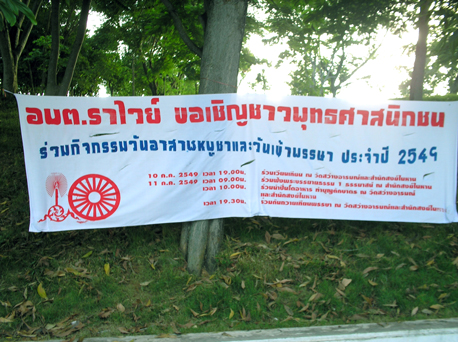
ไปเจอ [ฟอนต์ iannnnn] มา
ไปเจอมาด้วยคน
สถานที่ แถวๆหาดราไวย์ ภูเก็ต เจอเมื่อวันเสาร์
เ็ห็นว่าไกลดี และเป็นสิริมงคลดี
เพิ่งเจอเมื่อวานซืน โฆษณาของรพ.กรุงเทพคริสเตียน เขาใช้iannnnnUBCกัน... เอามาแผ่นนึง เดี๋ยวไปถ่ายรูปก่อน
แล้วก็อีกอัน SOS เจอบนแผ่นรองแก้วMK
ไปเจอหนังสือกล่องบุญ (Boon Box) มา
ใช้ฟอนต์พี่แอนด้วย
แล้วก็ใช้ฟอนต์สามด้วยแหละ  :25:
เห็นเหมือนกัน Boon Box แต่มันเป็นกล่องไม่ได้เป็นหนังสือ  :08:
เราซื้อมาข้างในมันเป็นหนังสือกล่องบุญน่ะ
แต่มีกล่องใส่พร้อมกับปากกาไว้บันทึกการทำความดี